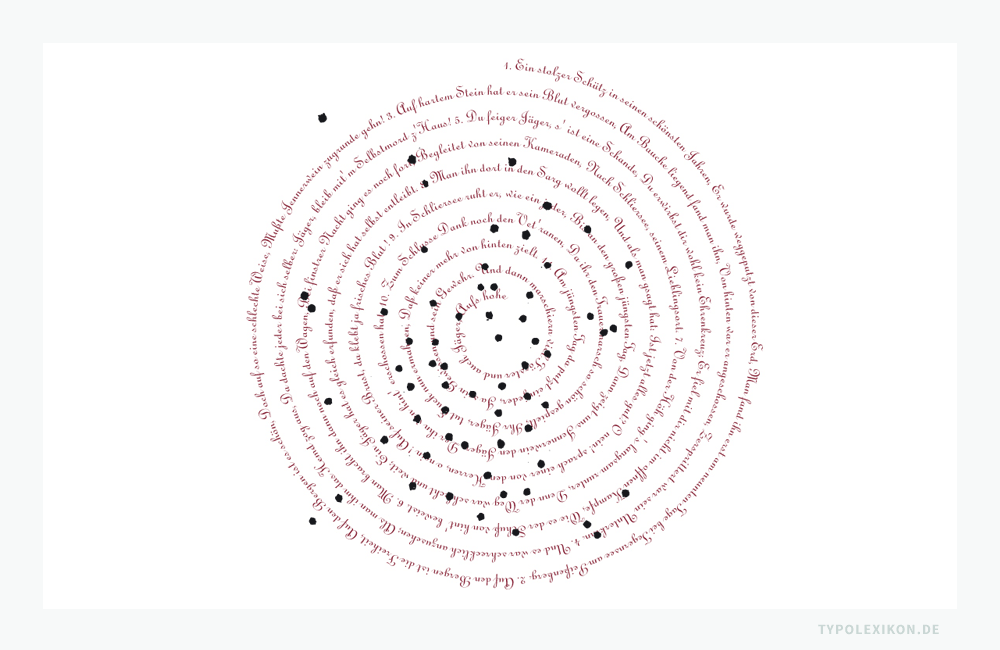
Formsatz
Schriftsatzart; Schriftsatz, dessen makrotypografisches Gesamtbild eine in sich geschlossene geometrische Figur oder freie Form ergibt, die auf dem Umriss einer konturierten Fläche oder einem Textpfad (Pfadtext) basiert. In der Typografie wird zwischen »Kontursatz« und »Freier Formsatz« unterschieden.
Beide Arten des Formsatzes wurden bereits in der Kalligraphie – vor Erfindung des Buchdrucks durch Johannes Gutenberg (um 1400–1468) – als grafisches Stilmittel in der Buchgestaltung angewendet. Von der Prototypografie wurde technisch bedingt allerdings nur der Kontursatz adaptiert, um anfänglich händisch ausgezeichnete Initialen, später um Bildmotive, z.B. Illustrationen oder Fotos, innerhalb eines Satzspiegels bzw. Gestaltungsrasters zu konturieren.
Kontursatz von Johannes Gutenberg (um 1400–1468). Abbildung: Faksimile einer 42-zeiligen Gutenberg-Bibel. Original gedruckt von Johannes Gutenberg in Mainz um 1455. Quelle: New York Public Library, 2009.
In der Typografie und artverwandten grafischen Druckverfahren wurde der Freie Formsatz als künstlerisches Ausdrucksmittel jedoch erst Ende des 19. Jahrhunderts durch neue grafische Reproduktions- bzw. Drucktechniken möglich und mit der »Kunsttypografie« bzw. der »Typografik« der 1920er Jahren populär.
Freier Formsatz in Form einer Spirale, der eine Zielscheibe darstellt. Beispiel gesetzt in der Linoscript von Morris Fuller Benton (1872–1948) auf einem Textpfad mit Adobe Illustrator®. Reinzeichnung: Wolfgang Beinert, Berlin. www.typolexikon.de
Freier Formsatz in Form einer Spirale, der eine Zielscheibe darstellt. Beispiel gesetzt in der Linoscript von Morris Fuller Benton (1872–1948) auf einem Textpfad mit Adobe Illustrator®.
Heute gehört Formsatz jeglicher Art zum technischen Standardrepertoire einer jeden Grafik- bzw. DTP Desktop Publishing Software, z.B. InDesign® oder Illustrator® von Adobe®.
In der Webtypografie besteht seit CSS3 Cascading Style Sheets 1)  die Möglichkeit, den Umfluss von Texten an unregelmäßigen Formen, z.B. Kreisen, Ellipsen und Polygonen, durch Shape-Eigenschaften zu definieren.
Beispiel einer Shape-Eigenschaft in einem CSS, mit der der Text um einen Kreis fließt.